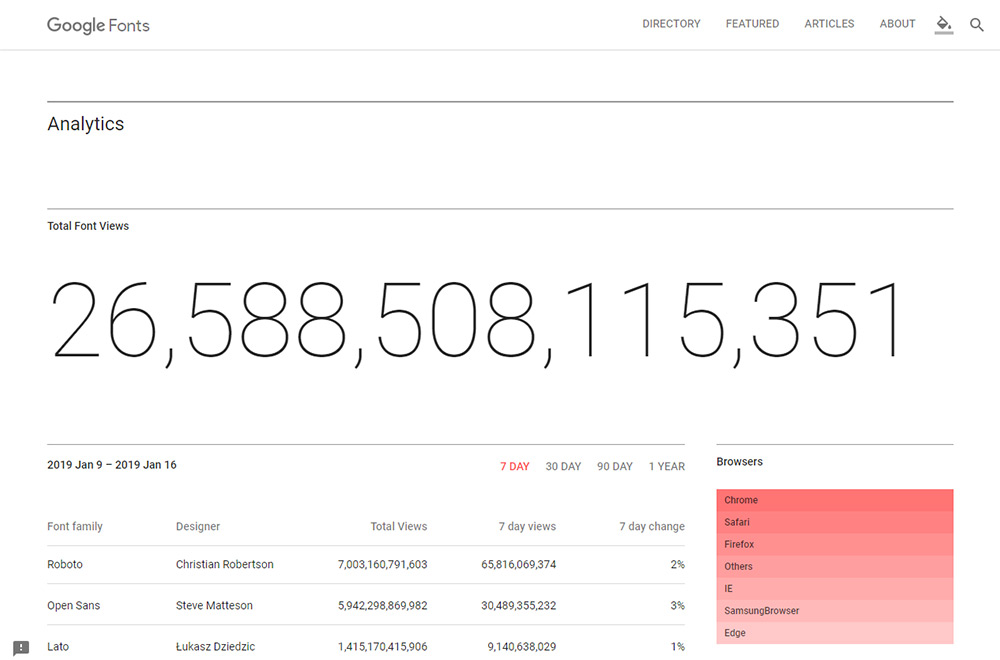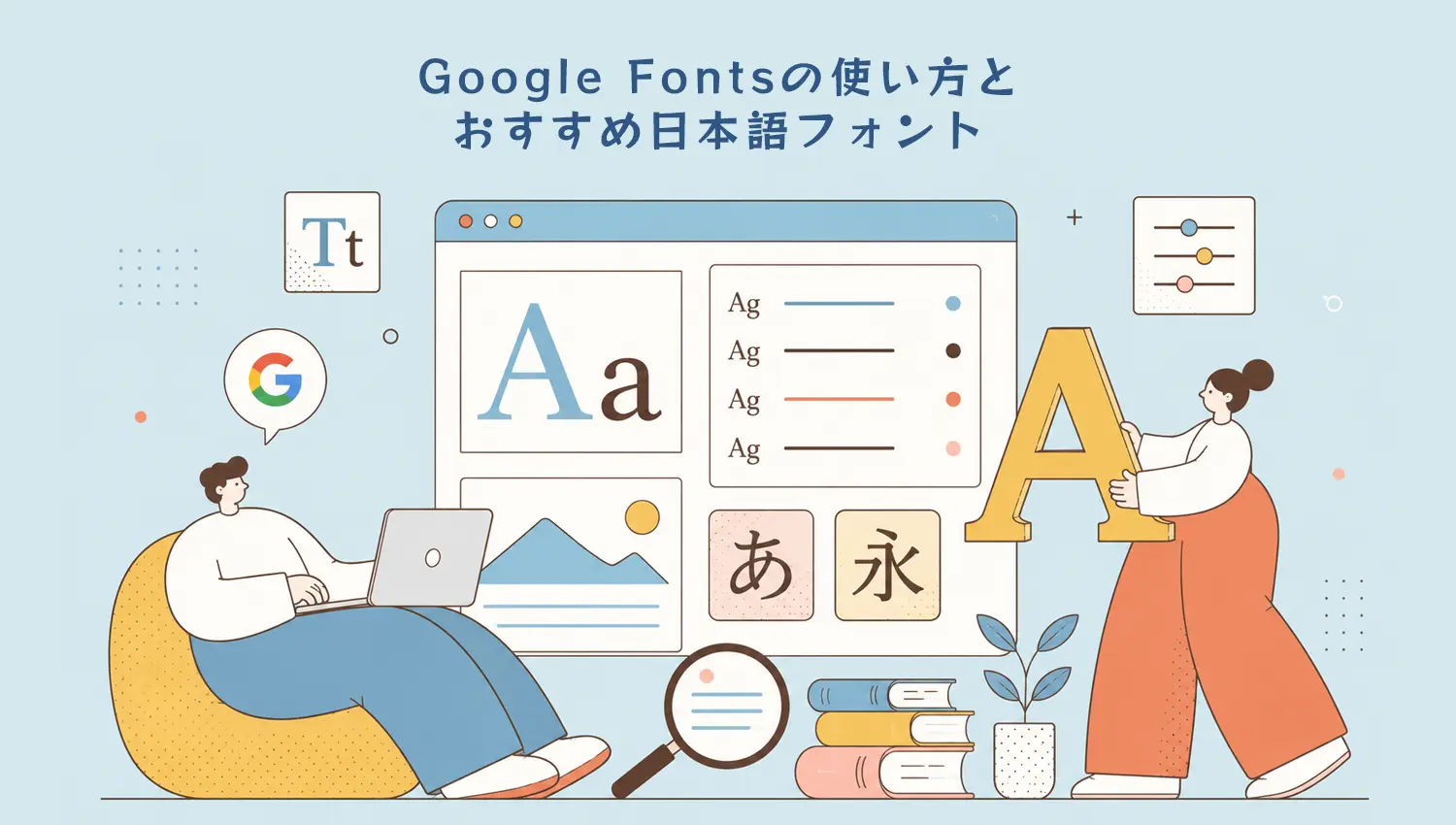
Googleフォントとは
Google Fontsは2010年にリリースしたGoogleが提供する、無料で利用可能なフォントのディレクトリーサービスです。Googleのサーバーからフォントデータを読み込んでWebページにフォントを表示できるWebフォントで世界各国で利用されています。
日本語フォントについて
日本語フォントを使用できることは便利なことですが、デメリットもありますので理解しておきましょう。日本語フォントは英語フォントより文字数が多いのでファイルサイズも大きくなります。英文フォントですとアルファベット・英数・記号合わせて100文字程度ですが、日本語はひらがな・カタカナ・英数・記号、漢字でJIS第1水準漢字だけでも2,965文字あります。表示速度の面でも日本語フォントを複数使用することは避けた方がよいでしょう。また、日本語フォントは太さ(ウエイト)が何種類か用意されてますが、全種類選択すると読み込み速度が遅くなるので注意が必要です。
日本語のおすすめGoogleフォント
Googleフォントの日本語フォントは当初は6種類のみでしたが、現在では57書体(2022年4月現在)となっています。2021年にフォントワークス、2022年にはモリサワのユニバーサルフォントが提供され、使用できるフォントの幅も広がりました。Noto Sans JPを中心にWebサイトで使用している例も多く見かけますが、ゴシック体・明朝体の他にも特徴のあるデザインフォントがありますので用途によって使い分けしてみましょう。数ある日本語フォントからおすすめのGoogleフォントを紹介します。
ゴシック体フォント
Noto Sans JP
GoogleとAdobeが共同開発し、2014年にリリースされたオープンソースの日本語フォント。ウェイトは6種類
BIZ UDPGothic
モリサワの読みやすく使いやすいように設計されたユニバーサルデザインフォント。ウェイトは2種類
M PLUS 1p
フリーフォントで有名なM+ FONTSのWebフォント版。漢字は直線的で、仮名は丸みのあるドッシリとした日本語フォント。ウェイトは7種類
Kosugi
フォントサイズを変更しても読みやすいフォント。ウェイトは1種類
M PLUS Rounded 1c
M PLUS 1pフォントの丸ゴシック体。ウェイトは7種類
Kosugi Maru
Kosugiフォントの丸ゴシック体。ウェイトは1種類
Kiwi Maru
マメロンフォントをベースに文字側部分を少し丸めた加工したキウイ丸フォント。ウェイトは3種類
Dela Gothic One
横長でどっしりした太いゴシック体フォントのデラゴシック。ウェイトは1種類
DotGothic16
ドットで構成されたデジタル風デザインフォント。ウェイトは1種
明朝体フォント
Noto Serif Japanese
Noto Sans JPと同様の明朝体。ウェイトは7種類
BIZ UDPMincho
モリサワの読みやすく使いやすいように設計されたユニバーサルデザインフォント。ウェイトは1種類
Shippori Mincho
うっとりするような明朝体を目指して制作した、オールドスタイル明朝体。ウェイトは5種類
Hina Mincho
ひな明朝は古風でかわいらしく品のある雛人形をイメージした明朝体フォント。ウェイトは1種類
手書風フォント
Klee One
鉛筆やペンなどを使って書いた手書き風文字のような印象を与える楷書系硬筆体フォント。ウェイトは2種類
Yomogi
極細で個性が強く、それでいて可読性の高い手書き風フォント。ウェイトは1種類
Yusei Magic
油性マジックで手書きしたようなデザインフォント。ウェイトは1種類
Hachi Maru Pop
70~80年代に流行った丸文字をイメージしたキュートな丸ゴシック体。ウェイトは1種類